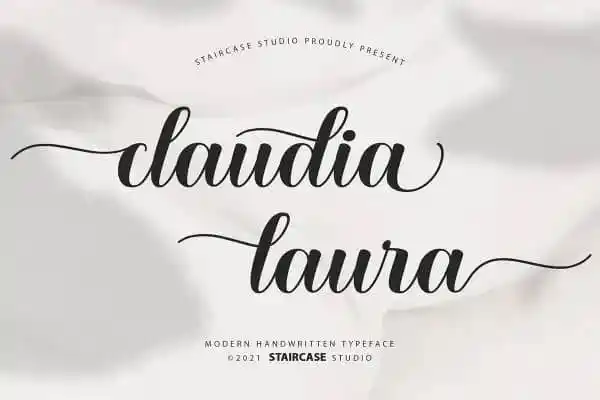
Claudia Laura Calligraphy Font
A Claudia Laura Calligraphy Font é uma elegante escolha para quem busca adicionar um toque delicado ao seu trabalho designístico. Manufacturada pelo Staircase Studio, esta tipografia moderna e criativa apresenta linhas de alta contraste. Ideal tanto para projetos pessoais quanto para o desenvolvimento de logotipos ou marcas, ela é perfeita para diversos ambientes, desde roupas têxteis até materiais publicitários e panfletos. Suave mas poderosa, esta fonte atende a um leque variado de necessidades gráficas. Seja para criar uma identidade visual única ou para tornar seus designs mais impactantes em projetos digitais, a Claudia Laura oferece tanto versatilidade quanto estilo elegante. Sempre fiel à sua essência minimalista e contrastada, esta fonte é um excelente recurso para designers gráficos em busca de uma solução criativa e sofisticada que se adapta a qualquer projeto de design.